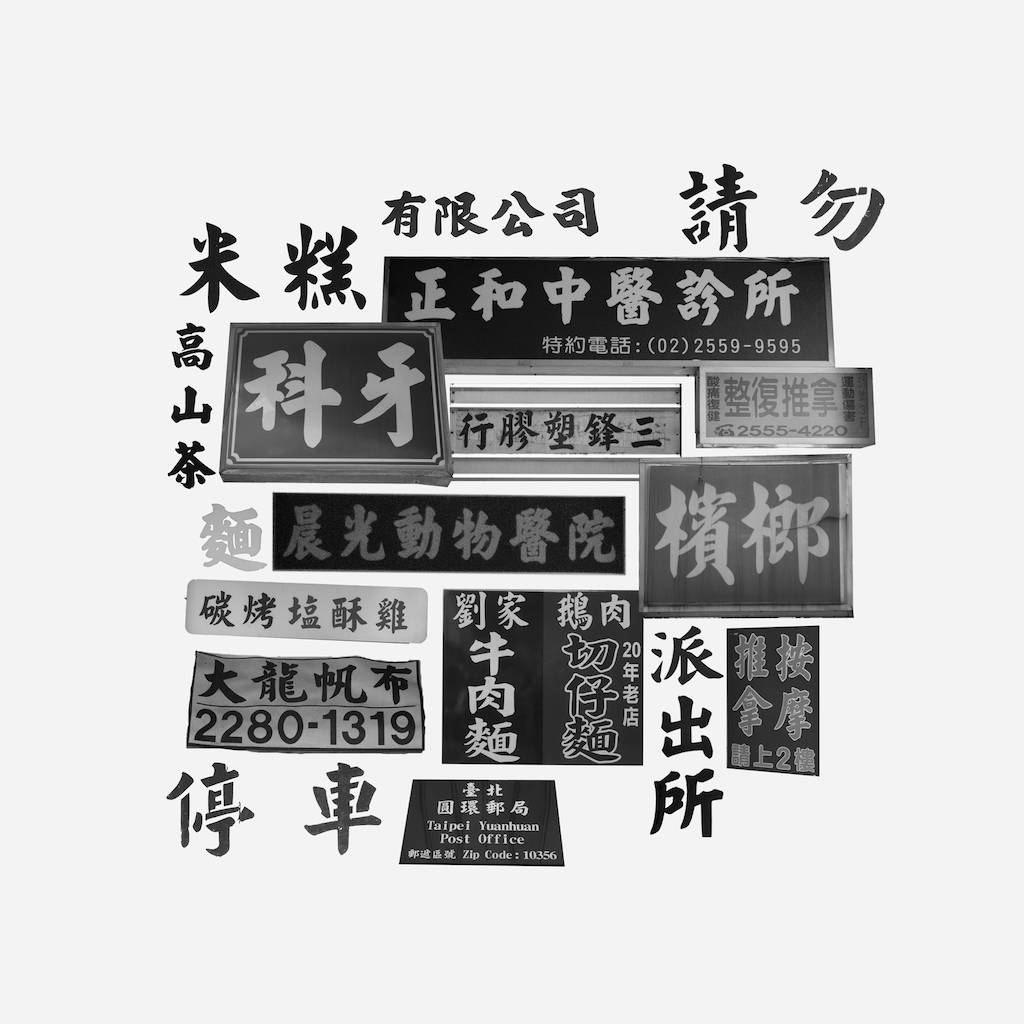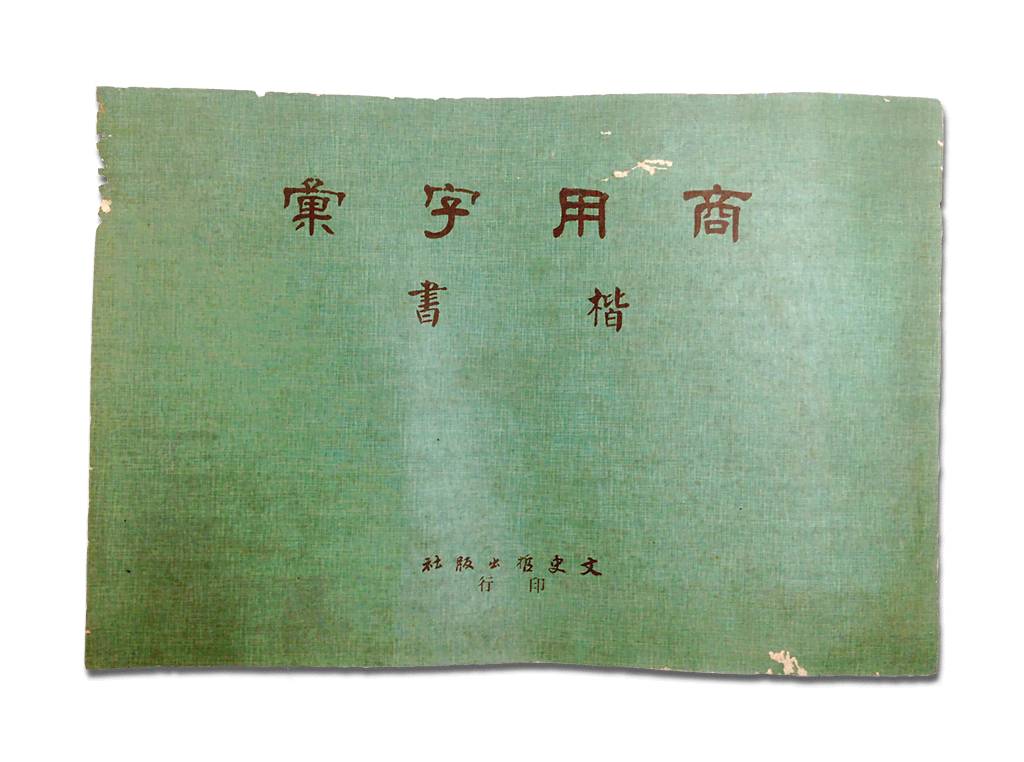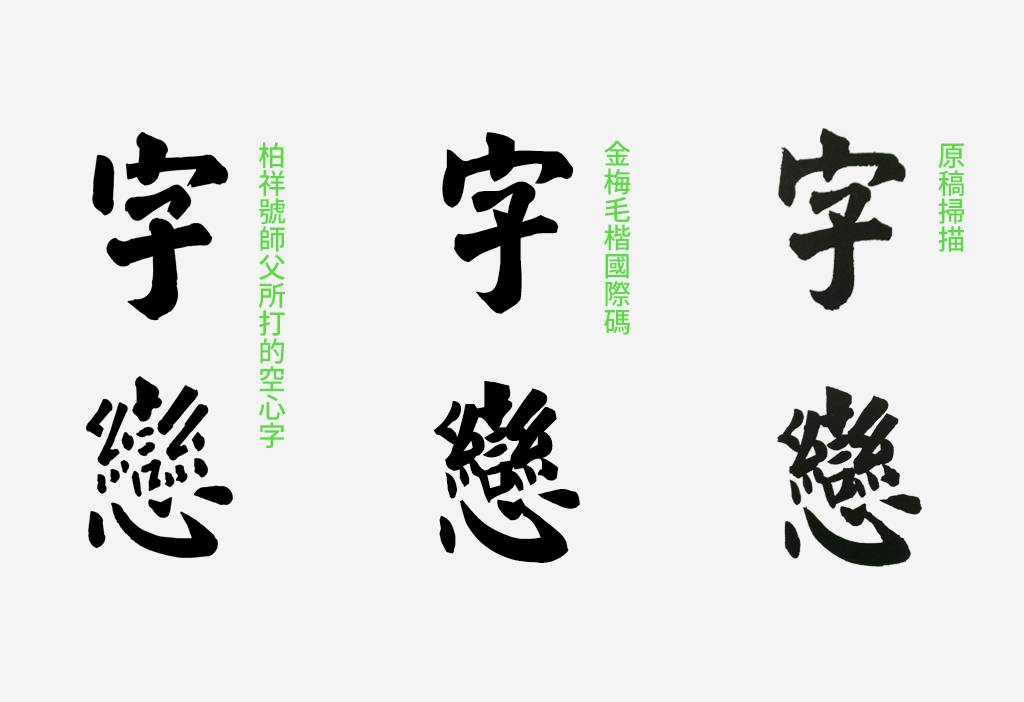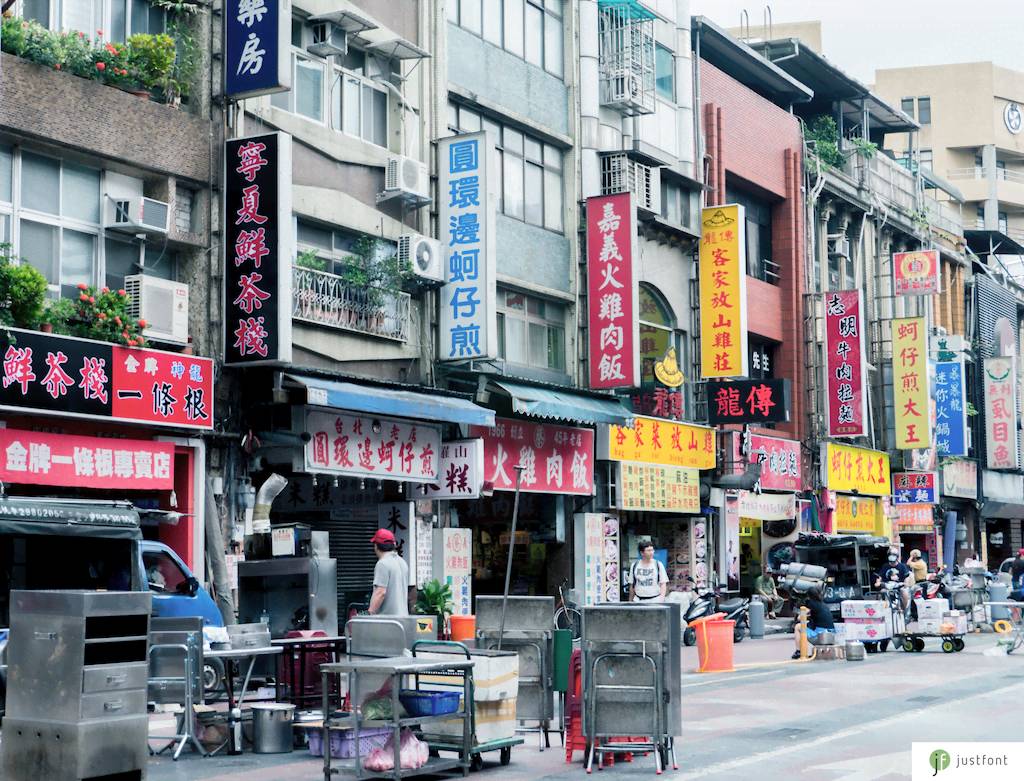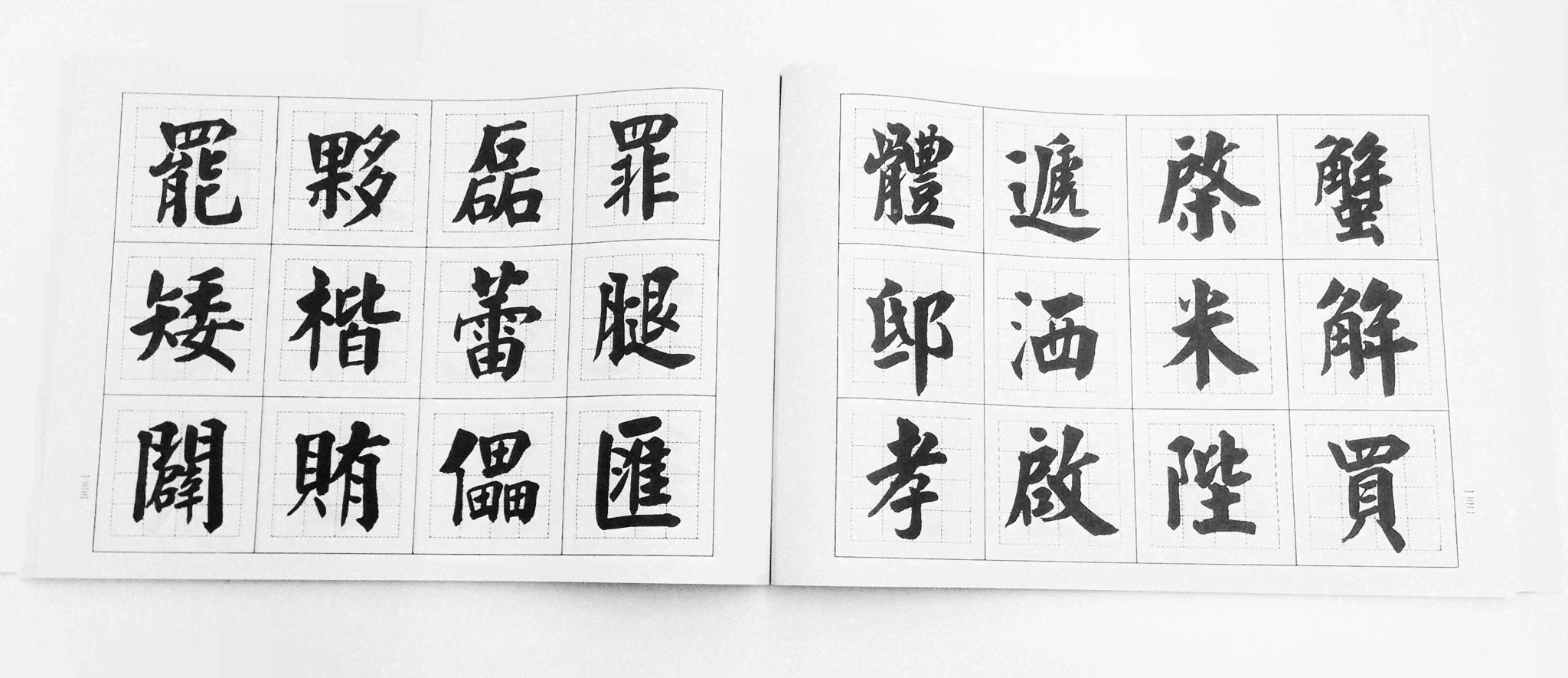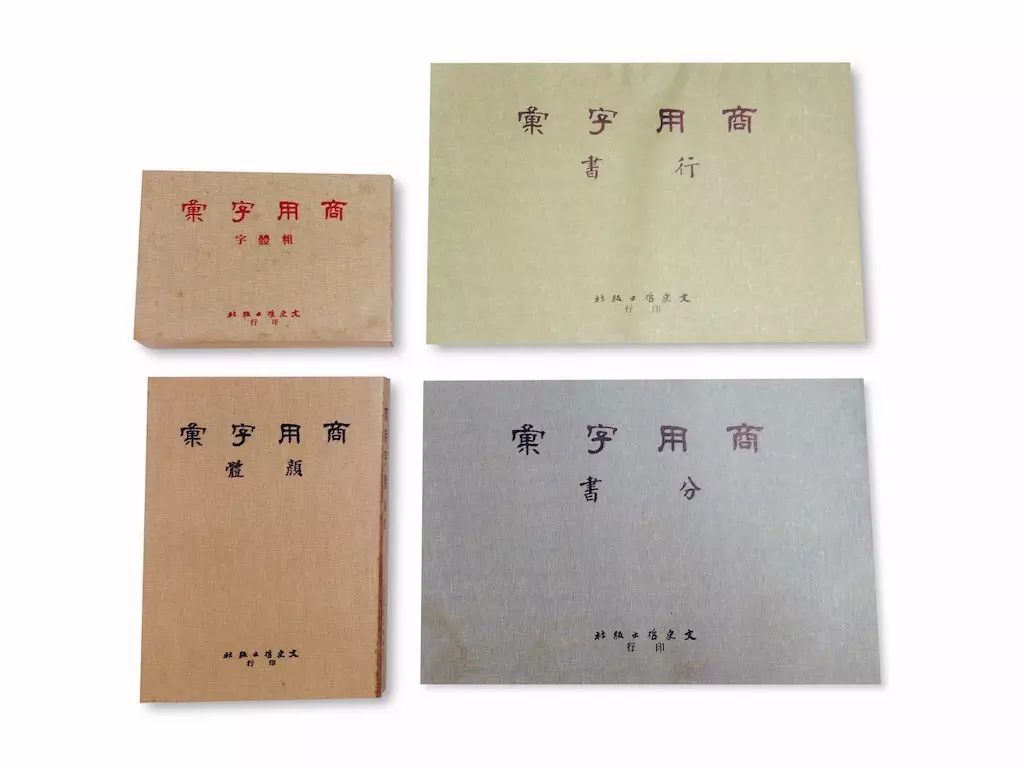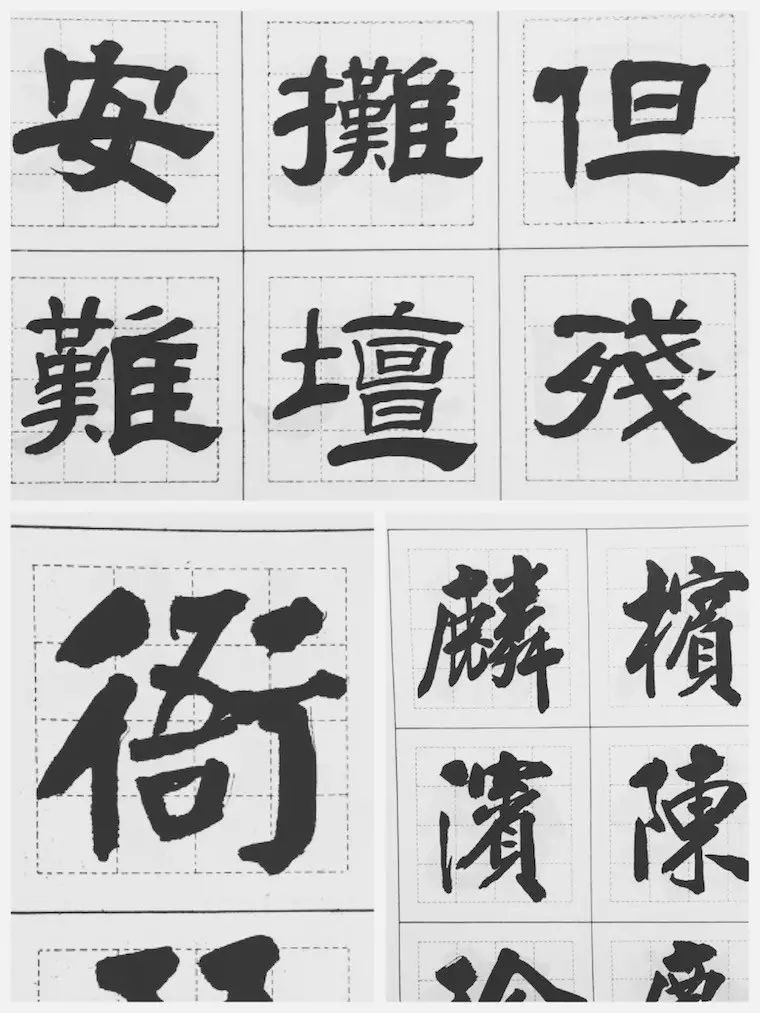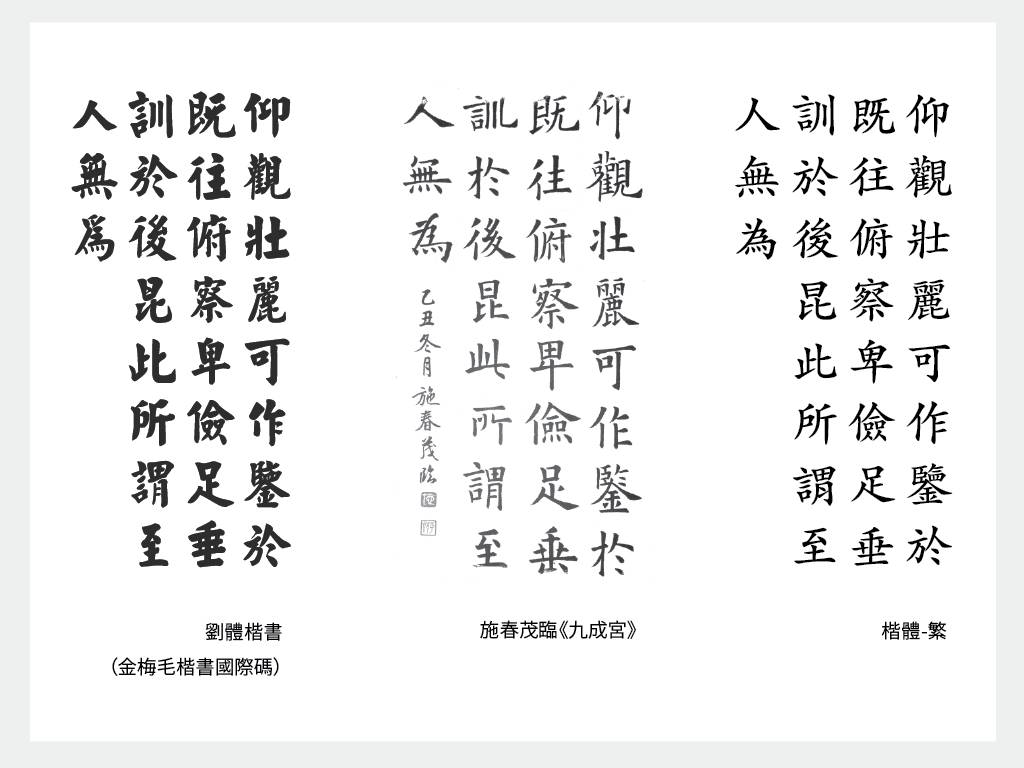
那些让人想到“台湾”的字体
一早出门,门口停了台货车,货车上的水果纸箱都是这个字体。中午出去吃饭,小吃摊的招牌也是这个字体。下班后去看中医,药袋上也有。晚上去倒垃圾,垃圾车外壳又是它。去买宵夜,「盐酥鸡」八成也是这字体。顺道去五金行买个水管,一瞥就知道是五金行。偶尔上街抗个议,警备车上也是这个字体。我们还可以一直举例下去。
有人喜欢,有人不喜欢。但选台湾代表字型若只看使用率的话,《商用字彙》的楷书应该能高票当选。
不久以前,我们以为大致不脱文鼎、金梅或中国龙三家公司都曾出品的「毛楷」类字型。前年台北市长选举时,神通广大的乡民还找到了「经典繁毛楷」做成文创商品。这些字型在骨架与笔形上太过神似,可能是互相「参考」来「参考」去的缘故,原著应已不可考。
直到有一天,我们在大稻埕专刻铁皮空心中英文字的「柏祥号」发现一本书,把我们都吓坏了。
本来就一直很好奇,为什麽打铁出来的字长得都很像「毛楷」,莫非师傅也套字型去打?。想请师傅帮我们打「字海」一探究竟,结果师傅说他不会打「海」,原因是因为字帖上没有。
什麽?师傅?你说什麽字帖来著?
曾经,招牌店必备的《商用字彙》
民国 71 年版《商用字彙》楷书篇内页
那本字帖是《商用字彙》楷书篇。由文史哲出版社印行,年代是民国七十一年,也就是还没有个人向量电脑字型的年代。原著为刘元祥先生。当下我们只知道这麽多而已,但翻著翻著,实在无法不惊呼:「天啊,找到了。」
文史哲出版社裡通常不会有人在那边对著书本哇哇叫。顾店的总经理也有点摸不著头绪,为什麽要买这麽久以前的招牌店字帖呢?但热心的她一边招呼著一边说,这裡还有其他系列呢。
什麽啊啊啊啊竟然还有系列。
《商用字彙》不只有「楷书」篇,还有「颜体(颜真卿样楷书)」、「分书(隶书)」、「行书」。一翻开,果真也是招牌上很常见的字体。没想到竟然在这裡一网打尽,全是同一个人写的。
如果你长期生活在台湾,一定对这些字体不陌生
文史哲出版社彭正雄老板说,这些字帖以前几乎每家招牌店都有。这系列作品最早可以追溯到民国六十年代,也就是 1970—1980 之间。写作者刘元祥先生自己先付梓,后来交给彭老板的文史哲出版社印行再版。据彭老板表示,这套书一本卖 500 元新台币(当时一碗阳春麵是 1.5 元),共卖了 2000—3000 本左右。照这个规模推估,差不多大多数招牌店都买了吧。这还无法计算盗印版。据闻盗版一本 300 元,所以卖得更好。
刘元祥先生
彭老板想了一下,刘元祥先生大约在 2001 年左右就过世了,我们已无法获得第一手消息。据《商用字彙》上的书籍资料,刘元祥是山东潍县人,民国 13 年生(1924)。
曾经在台北市政府替长官写书法(婚丧喜庆红白帖、匾额、輓联类)。也有许多熟门熟路的人会私底下求字于他。彭老板因为印书的关系,看到书封上的字很喜欢,便透过印刷厂找到了刘元祥先生,为文史哲出版的书题字。听到这裡,或许会以为他是位写字匠,其实不然。
台大历史系的阎鸿中老师曾跟随刘元祥先生学习书法三十馀年,忆起恩师,仍景仰万分。刘元祥,字大镛,礼貌上应该称呼为刘大镛先生。毕业于济南师范学院,二次大战时加入中国青年军,随国民党政府来台后退伍。曾在中学任教,但与体制理念不合,遂不愿再执教。偶然帮开招牌店的朋友写字,意外成名,就渐渐以此为生计。
老古出版社印行的《佛门楹联》由南怀瑾先生撰联,书封上写刘大镛敬录,阎鸿中老师认为较近于他的日常书写。彭老板也说,他著作署名是有区隔的。书法类作品留的是字「大镛」,《商用楷书》登记著作权,所以留本名。
民国六十一年起,应南怀瑾先生之邀,刘大镛在其「东西文化精华协会」教书法,前后有三年左右。这是他唯一一次开班授课。阎鸿中上课时只有十岁,但往后三十年,仍不时向刘元祥请益书法。回忆起老师,阎鸿中说,刘大镛历临碑帖,相当熟悉古人底蕴,用功甚勤。然而他纯为自娱,也是个人修养的方式。没有办过展览,也没有卖过字画,实在是因为生活所需,才靠题字赚钱。当时,一段封面题字,可以收新台币 10 块钱。彭老板与刘大镛来往多次,遂成好友。刘先生索性不收钱了。
或许一方面是想流传自己的作品,又想以此带来一笔收入,所以刘元祥在民国 60 年代自己刊印了《商用字彙》套书。后来找上了彭老板替他再版。彭老板一口答应了。售价 500 元一本,300 元归作者,200 元归出版社。
刘大镛先生上课时示范的笔迹。阎鸿中提供
介在印刷字型与书法之间
不过,据阎鸿中表示,刘大镛时常感慨无形中受到工作影响,书艺不能免俗,颇为遗憾。艺术家对自己的要求严格,是可以想像的。但既然业界採用率高,后来他也愿意无偿让电脑字型业者使用,就当作是推广书法艺术。或许因为如此,他的四套书法体才成为全台湾最常见的招牌字型。
有些书法老师可能一看到就嫌呆板,嫌搭配起来没有书法应有的美,却又同意这些字体适合招牌与印刷。甚至也不会否认,《商用字彙》系列其实是「商业设计」,或根本该说是「准字型」作品。
以《商用字彙》楷书而言,每个字都框在同样的范围裡、视觉上几乎一样大,这在书法上不必然是件好事。书法较讲究变化,行气参差,有飞舞的感觉。但这可能无法满足大部分商家招牌的需求。这套字其实是以标题、看板文字角度出发「设计」的。跟做字型的原则很像,要考虑到排列组合,不能有些字特别突出,或有些特别小,要讲究饱满、显目、易读、而且预先假设到任何场合都能用。
从下图的比较我们可以观察到中间施春茂先生所临的《九成宫醴泉铭》是结构形状变化最明显的。以一行行来看,会觉得比较有错落起伏的感觉。书法裡的「行气」就是这个意思。而字型化的刘体楷书,单字形状变化较少,不过再比较右边的「楷体-繁」(接近标楷体的电脑楷书字型),刘体楷书变化又更丰富了一些。
比较电脑化刘体楷书、书法《九成宫醴泉铭》以及 Mac 内建字型「楷体-繁」
若把三种字体变成纯粹的外框,会发现书法《九成宫》最形状变化最灵活,有行气。
楷体-繁相较之下每个字的轮廓较为接近。而刘体楷书则介于中间。
非战之罪
虽然有书法的基因,不过还是会有人觉得刘体楷书失去了书法应有的气息。尤其在许多卡典西德看板上(卡典西德是招牌割字最主要的材质),看起来甚至更僵化了。不过,字体要从纸本转换到任何其他媒介上,都存在著鸿沟,不只是数位化会遇到这个问题。
就拿从前招牌店是如何运用《商业字彙》来说好了:透过简单的设备,招牌店可以把字帖直接投影在看板上,依样描绘;刻空心字的师傅用描图纸也能複製字的轮廓。电脑字型版本则可能是原样直接扫描再透过特定方式转成贝兹曲线的。但是,投影法得到的是模糊的轮廓,描绘的师傅就像在玩著色书一样,还是有很多需要自己填补跟诠释的地方;刻空心字则是要打穿金属板,也很难 100% 重现毛笔的笔触。而大部分数位化后的刘体楷书,因为 auto-trace (自动描绘)设定不同,也不一定能完整表现原本丰富的细节。
光是比较线条边缘细节的丰富程度,就会发现任何一种再现方式都是重新诠释的
而这系列作品的影响力,正是一次次複製中所堆叠出来的。去到新加坡、柬埔寨,只要有华人街的地方,都能在招牌上看到他的字。但我们也得清楚一件事:绝大部分複製方式都难以 100% 原汁原味重现,《商用字彙》仍仅是「准字型」作品。总之,媒介的改变、数位化描绘的过程,都可能加入不同的诠释。